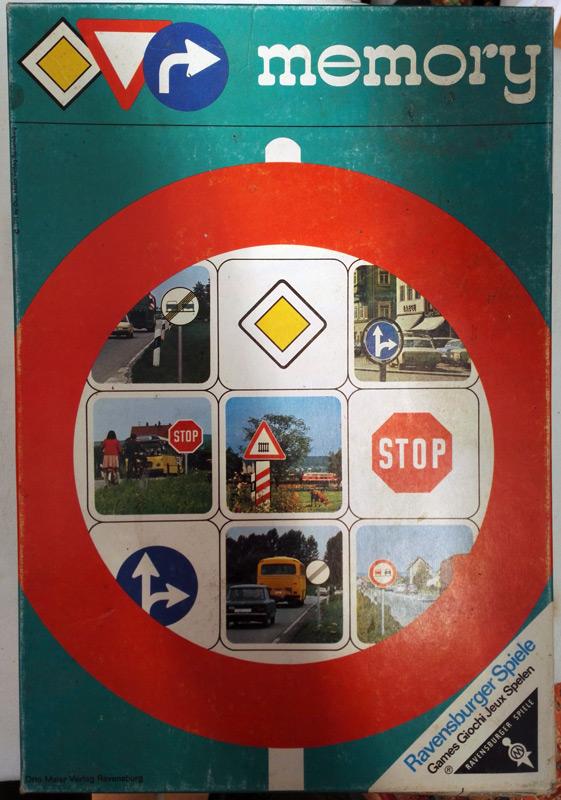
Auf dem Dachboden entdeckt! Ich kann es nicht datieren,
aber es handelt sich um ein Memory Spiel von Ravensburger.
Besonders "interessant" fand ich die Schriftart in der das
Wort "memory" rechts oben geschrieben wurde ... sowie
(wohl nochmal zur Verdeutlichung) das "Logo" dazu,
links daneben, bestehend aus drei Verkehrsschildern ...
aber irgendwie hat es was, find ich ... :p
Warum nur denke ich hier an Captcha? Klicken Sie alle Bilder mit PKWs...
Ich schätze mal, das Spiel ist aus 1971, als die neuen Verkehrsschilder, u.A. die Vorfahrtstraße mit innen gelb, statt mit rotem Rand, eingeführt wurden.  Die "memory" schrift ist auch typisch 70er.